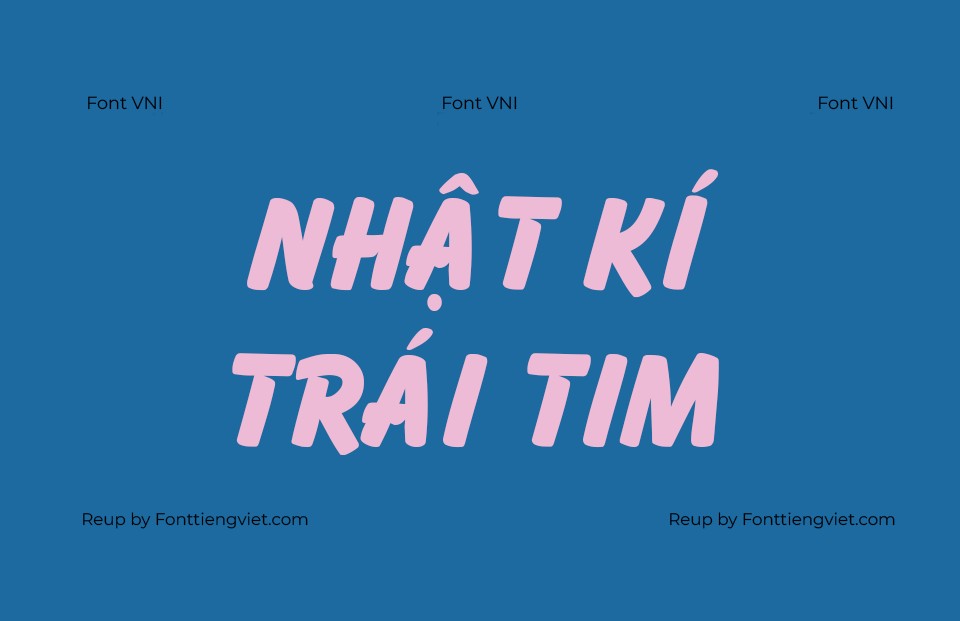
Font Việt hoá VNI Bandit
Giới thiệu về Font Việt hoá VNI Bandit
Trong thế giới đồ họa hiện đại, việc tìm kiếm một bộ Font Miễn Phí có phong cách mạnh mẽ và độc đáo luôn là ưu tiên hàng đầu của các nhà thiết kế. Font Việt hoá VNI Bandit nổi lên như một lựa chọn hoàn hảo cho những ai yêu thích sự phá cách, cá tính nhưng vẫn đảm bảo tính ứng dụng cao. Đây là bộ font được chuyển đổi sang bảng mã VNI, giúp người dùng dễ dàng gõ tiếng Việt trên các phần mềm thiết kế cũ hoặc các công cụ văn phòng truyền thống. Với đường nét dày dạn và dứt khoát, bộ chữ này mang lại cảm giác năng động, rất phù hợp cho các tiêu đề lớn hay biểu ngữ cổ động.
Đặc điểm nổi bật của Font Việt hoá VNI Bandit
Thiết kế đậm chất nghệ thuật
Đặc trưng của Font Việt hoá VNI Bandit nằm ở cấu trúc chữ cái vững chãi và khoảng cách giữa các ký tự được tính toán kỹ lưỡng. Phong cách này gợi liên tưởng đến các tác phẩm graffiti hoặc poster phim hành động, giúp tác phẩm của bạn thu hút ánh nhìn ngay lập tức. Các dấu tiếng Việt được tinh chỉnh khéo léo để không làm mất đi vẻ cân đối của mặt chữ gốc.
Tính ứng dụng linh hoạt trong học tập
Đối với các bạn học sinh và giáo viên, bộ font này là công cụ đắc lực để trang trí bảng tin, làm bìa báo tường hoặc thiết kế các slide bài giảng sinh động. Sự rõ ràng của chữ giúp nội dung dễ đọc dù ở khoảng cách xa, đồng thời tạo nên dấu ấn riêng biệt cho các dự án sáng tạo học đường.